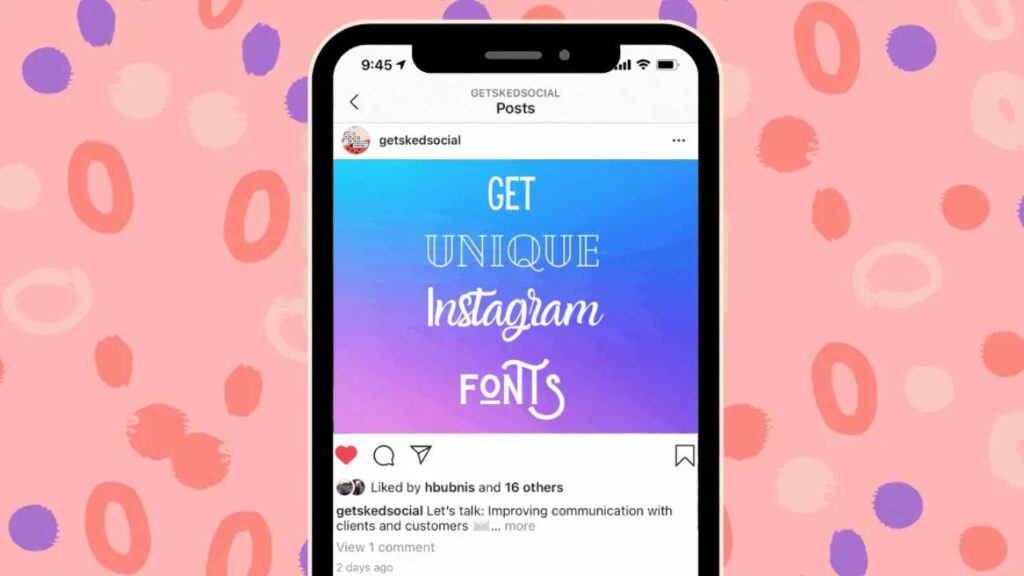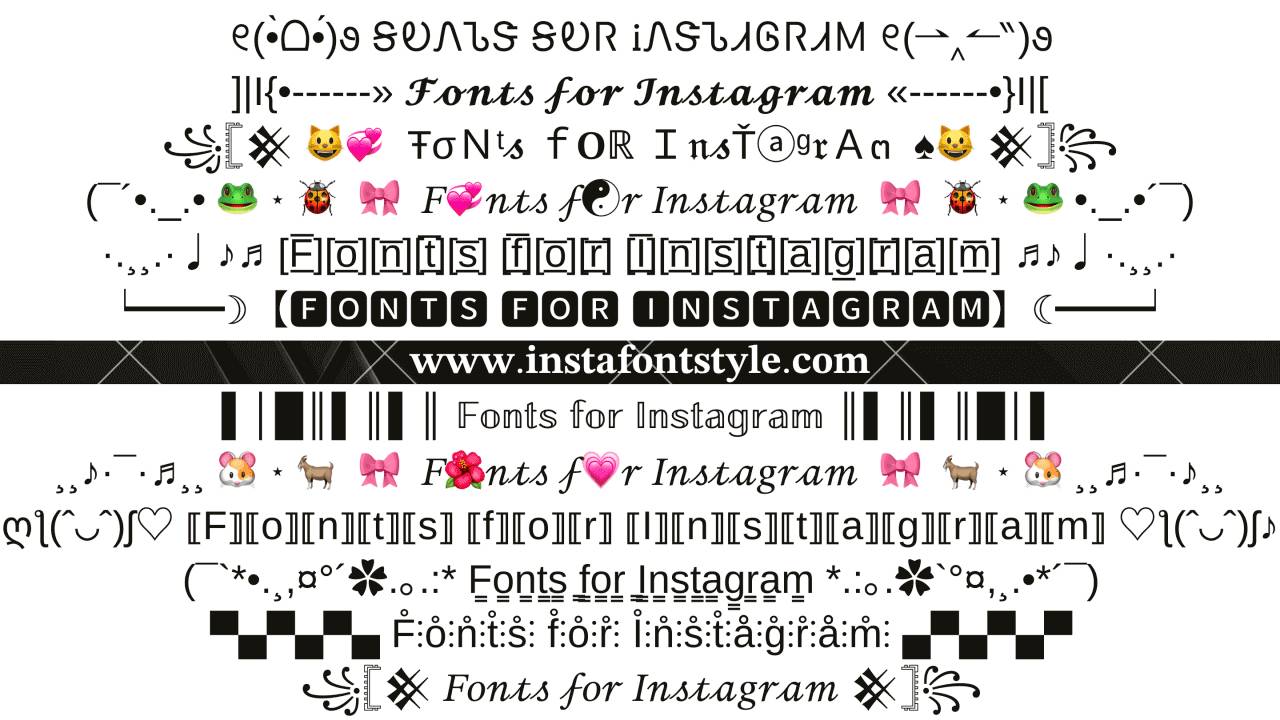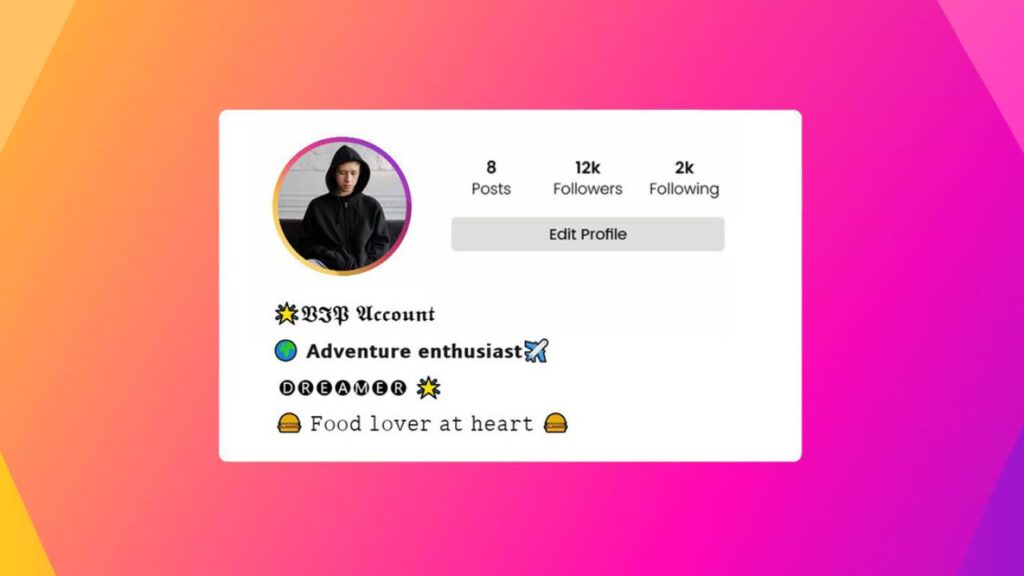
راهنمای کامل تغییر فونت اینستاگرام
تغییر فونت اینستاگرام، یکی از ساده‌ترین و در عین حال جذاب‌ترین راه‌ها برای شخصی‌سازی پروفایل و پست‌های شماست. استفاده از فونت‌های مختلف به شما این امکان را می‌دهد که محتوای خود را به شکلی جذاب‌تر و خاص‌تر ارائه کنید.
این تغییرات به ظاهر پروفایل شما جلوه‌ای منحصر به فرد می‌دهند و باعث جلب توجه بیشتر کاربران می‌شوند. در این مقاله از تکناک، به بررسی نکات مهم در تغییر فونت اینستاگرام و چگونگی استفاده از آن برای بهبود تجربه کاربری می‌پردازیم.
چرا تغییر فونت اینستاگرام مهم است؟
ابتدا باید بدانیم چرا تغییر فونت در اینستاگرام می‌تواند مفید باشد. اینستاگرام یک پلتفرم پررقابت است که هر روز میلیون‌ها پست، استوری و محتوا به آن افزوده می‌شود. برای جلب توجه کاربران و ایجاد یک پروفایل منحصر به فرد، باید از ویژگی‌هایی استفاده کنید که شما را از دیگران متمایز کند. تغییر فونت در بیوگرافی، پست‌ها و استوری‌ها یکی از این ویژگی‌ها است که به شما کمک می‌کند تا هویت خاص خود را در این شبکه اجتماعی ایجاد کنید.
با تغییر فونت، پروفایل شما به چشم کاربران خاص‌تر و جذاب‌تر خواهد آمد. این تغییرات به زیباتر شدن ظاهر پروفایل کمک می‌کند و تأثیر زیادی در جلب توجه و افزایش تعاملات با مخاطبان شما دارد. حتی در بیوگرافی، که اولین چیزی است که بازدیدکنندگان پروفایل شما می‌بینند، استفاده از فونت‌های خاص برایشان جالب و متفاوت است.